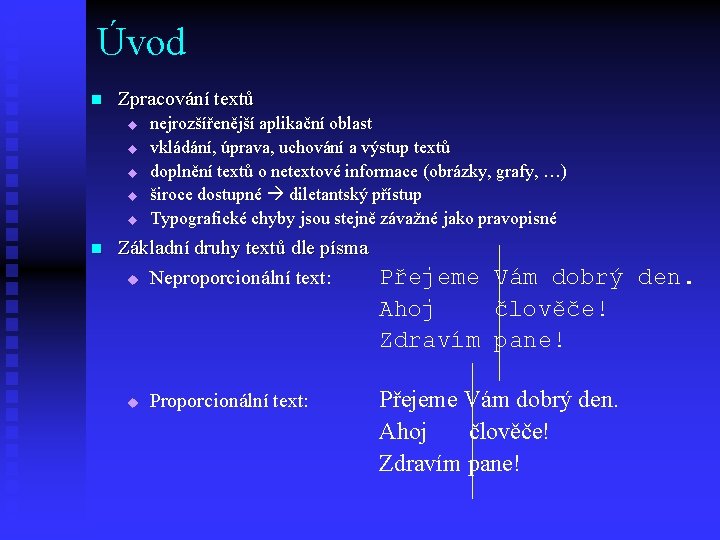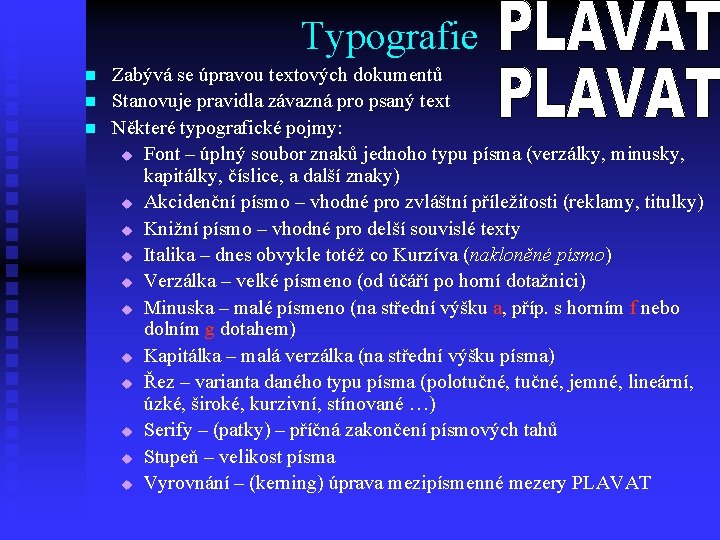
Zpracování textů počítačem Základy typografie
Úvod n Zpracování textů u u u n nejrozšířenější aplikační oblast vkládání, úprava, uchování a výstup textů doplnění textů o netextové informace (obrázky, grafy, …) široce dostupné diletantský přístup Typografické chyby jsou stejně závažné jako pravopisné Základní druhy textů dle písma u Neproporcionální text: u Proporcionální text: Přejeme Vám dobrý den. Ahoj člověče! Zdravím pane!
Práce s neproporcionálním textem n n n Každý znak zabírá stejné místo lze měřit délku řádků počtem znaků normalizovaná stránka (30 řádků po 60 znacích) Zarovnání jen na levý okraj Snadné zarovnání textů v tabulce Řádkování: 1, 1½, 2 (norm. str. má řádkování 2) Pravidla: u Odstavec začíná 5 mezerami u Po interpunkci 1 mezera u Mezera není před interpunkcí ani za otevírací a před uzavírací závorkou u Pomlčka k oddělení větných celků – z obou stran 1 mezera Pro práci s neproporcionálním textem se používají tzv. textové editory.
Práce s proporcionálním textem n Zcela odlišný způsob práce n Písmena seskládaná u sebe n Výhody: dobře čitelná slova n Programy pro práci s proporcionálním textem: DTP systémy u DTP pro sazečskou práci v tiskárně (profesionální) u DTP vzniklé vývojem textových editorů (chyby)
Typografie n n n Zabývá se úpravou textových dokumentů Stanovuje pravidla závazná pro psaný text Některé typografické pojmy: u Font – úplný soubor znaků jednoho typu písma (verzálky, minusky, kapitálky, číslice, a další znaky) u Akcidenční písmo – vhodné pro zvláštní příležitosti (reklamy, titulky) u Knižní písmo – vhodné pro delší souvislé texty u Italika – dnes obvykle totéž co Kurzíva (nakloněné písmo) u Verzálka – velké písmeno (od účáří po horní dotažnici) u Minuska – malé písmeno (na střední výšku a, příp. s horním f nebo dolním g dotahem) u Kapitálka – malá verzálka (na střední výšku písma) u Řez – varianta daného typu písma (polotučné, jemné, lineární, úzké, široké, kurzivní, stínované …) u Serify – (patky) – příčná zakončení písmových tahů u Stupeň – velikost písma u Vyrovnání – (kerning) úprava mezipísmenné mezery PLAVAT
Písmová osnova Akcentová dotažnice horní dotažnice verzálková dotažnice střední dotažnice účáří dolní dotažnice
Typ a stupeň písma n n n 4 kategorie: u Serifová (antikvy) – vedou oči po řádku u Bezserifová (grotesky) – kratší text, nadpisy u Lineární serifová (egyptienky) - příležitostně u Ostatní (zdobná apod. ) Vyznačení (zdůraznění významu textu) u Kurzíva u Tučný řez u Kapitálky (slavnostní ráz, nadpisy) u P r o s t r k á n í – u editorů se nepoužívá Stupeň písma: u obvykle 9 -12 bodů (cca. 10 – 13 pt. ) u 8 – Kolonel (noviny) 9 – Borgis (časopisy, knihy) u 10 – Garamond (knihy) 12 – Cicero (dětské knihy)
Zvláštní znaky n n Mezery u Mezislovní mezera – mezerník, pružná velikost, možnost zalomení textu u Nezlomitelná mezera – pevné svázání slov u Pozor na rozdíl: 13 % a 13% 12 ° a 12° Pomlčky u Spojovník (rozdělovník): žluto-zelený, Rimskij-Korsakov, dělení slov (je nejkratší a nemá kolem sebe mezery) u Pomlčka bez mezer: namísto slov až, až do a versus. Např. 6– 8, Sparta –Slavia (nesmí být na konci řádku) u Pomlčka s mezerami (k oddělení větných celků). Např. Udělal pro to vše – výsledek se dostavil. u Znaménko minus (koresponduje s šířkou číslice) Uvozovky u Počáteční „ a koncové“ (US: “uvozovky”) u Vždy bez mezery stejně jako závorky Další: O× 0 1×l
Sazba odstavců n n n Zarovnání: u doleva (na prapor vpravo) u doprava (na prapor vlevo) u na střed u na blok Oddělení odstavců: u odsazení (zarážka) v prvním řádku u odstavcové odsazení (svislá mezera mezi odstavci) u předsazení 1. řádku (např. u slovníkových hesel) u odstavce, které jsou součástí seznamů (výčtů) – odrážky a číslování t číslování: 1. , 1. 4. , IV, iv, a) Pro zarovnání do bloku se používají pouze mezislovní mezery. Typograficky správně: šedý odstavec, špatně: řeka. Švícko (parchant, sirotek): osamocený poslední řádek odstavce na nové stránce. Proklad (obdoba řádkování): vzdálenost účaří dvou po sobě jdoucích řádků na 120% bodové velikosti písma.
Stránka a publikace n n n n Zrcadlo: prostor pro vlastní text na stránce u horní okraj je zpravidla menší než dolní u vnitřní okraj (u hřbetu) menší než vnější Záhlaví: pro orientaci v textu (název kapitoly, článku, autor, číslo stránky) Zápatí: méně informací, obvykle jen číslo stránky Pravé stránky – lichá čísla 1 sloupec, více sloupců netextové objekty – jednotný ráz, problém obtékání Publikace: u Titul (obálka) i uvnitř dokumentu (na pravé stránce) u levá stránka prázdná – vakát u Vlastní text (předmluva, úvod, obsah, text členěný do kapitol) u Nadpisy kapitol – zřetelný systém (stupeň písma , příp. řez) u Zadní část: dodatky, rejstříky, tiráž (údaje o autorech, nakladateli, náklad. . . )
Rozdělení textových editorů – dle možností n Textový editor – program pro vytvoření, úpravy a tisk textových dokumentů. n Rozdělení (dle možností programu) u u Jednoduché editory neformátovaný text (znaky a konce řádků) t Pro psaní dávkových souborů t Pro psaní zdrojového textu programů (WWW stránek) t Př: Poznámkový blok (Notepad) Textové procesory t t Formátovaný text (font, typ, řez, velikost písma, zarovnání, řádkování) Vkládání netextových objektů (obrázky, tabulky, …) Pomocné funkce (kontrola pravopisu, synonyma, …) Př: MS Word, Word Perfect, …
Textové procesory – dle způsobu formátování textu n S přímým (vizuálním) formátováním u Princip WYSIWYG (What You See Is What You Get) t Formátovací příkazy se ihned provádí a výsledek se zobrazuje na obrazovce t Mezi zobrazením na obrazovce a vytištěným výsledkem jsou vždy rozdíly u Př: MS Word, Word Perfect, … n S kontextovým formátováním u u Formátovací příkazy se vkládají přímo do textu (obdoba HTML) Formátování se provádí až při tisku Menší a snadno přenositelné mezi platformami Př: TEX (LATEX)